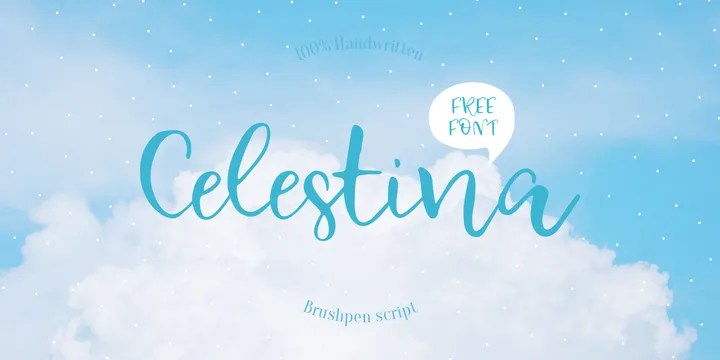
Descubra Celestina Script Font, uma elegante fuçã escrita a mão criada pelo designer 178-MC. Esta fonte é ideal para quem busca algo suave e envolvente para seus projetos gráficos, seja em blogs pessoais ou criações de arte handmade. Celestina, com seu estilo fresco e natural como gotas de tinta na folha de papel ou nuvens no céu, mantém o mesmo espírito nas letras curvas do tipo e nos pequenos torcúlas que adornam os caracteres. É perfeitamente adaptável tanto para a criação da famosa série de Moomins quanto para textos pessoais ou até mesmo quando você quer simplesmente se sentir bem. Celestina Script é uma opção fantástica para projetos variados, seja em cartões personalizados, editoriais de blog, arte digital handmade ou qualquer outro tipo de projeto. Seja uma frase única ou um texto completo, Celestina proporciona o toque final perfeito ao seu design. Aqui está uma fonte que não apenas expressará sua personalidade mas também irá trazer alegria para seus projetos.